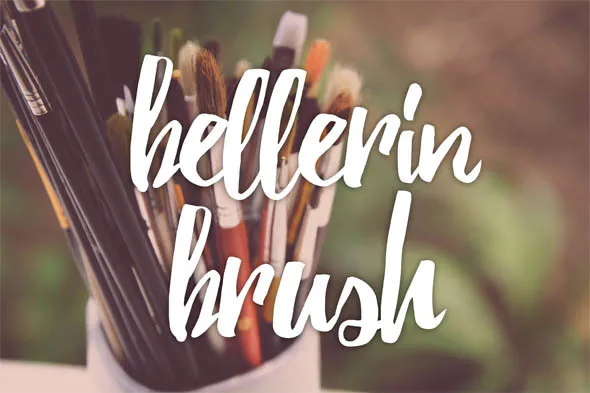
Bellerine Brush Font
A Bellerine Brush Font é uma elegante fonte de tração feita à mão com um peso forte acentuado por sua natureza serena e delicada. Seus traços fluidos são perfeitos para dar um toque romântico e encantador aos seus projetos gráficos, tornando-a especialmente adequada para aplicações como logotipos, rótulos de moda ou capas de livros. A Bellerine também se adapta bem para design de marcas, posts no Instagram e até mesmo camisetas personalizadas. Seu estilo fluido é perfeito para levar seu trabalho a um nível mais sofisticado sem abandonar a essência pessoal. Esta fonte é uma ótima escolha para quem busca algo único e envolvente em seus designs de marca ou conteúdo digital.